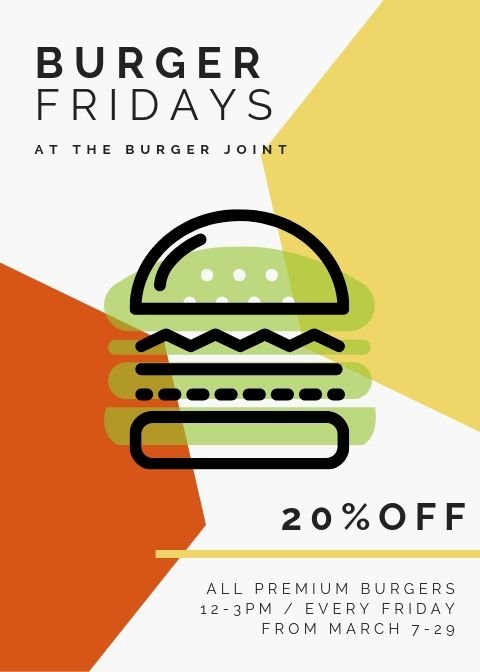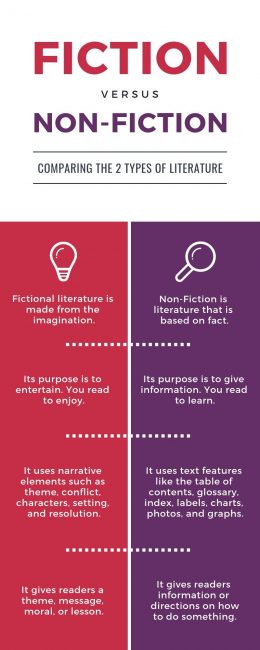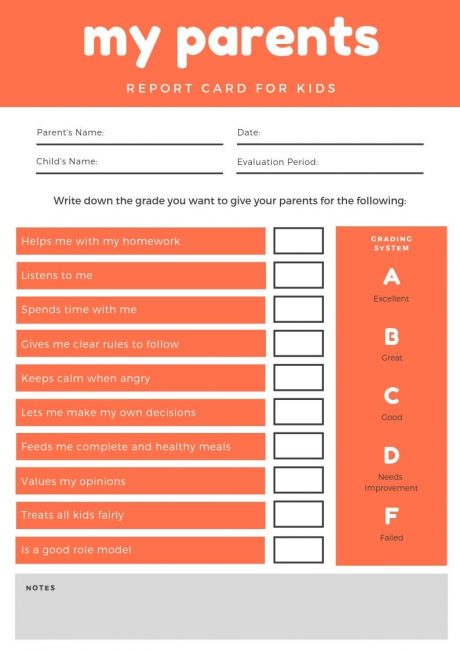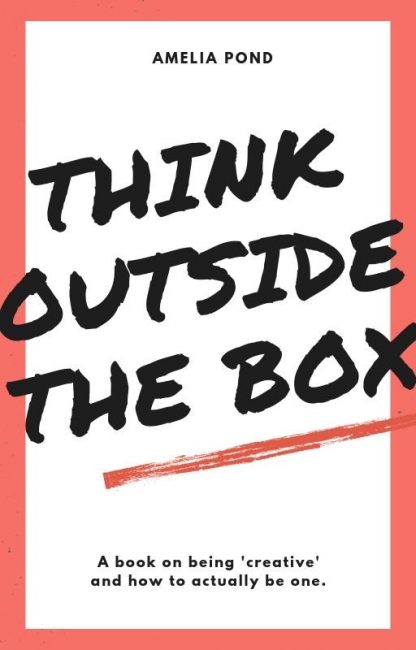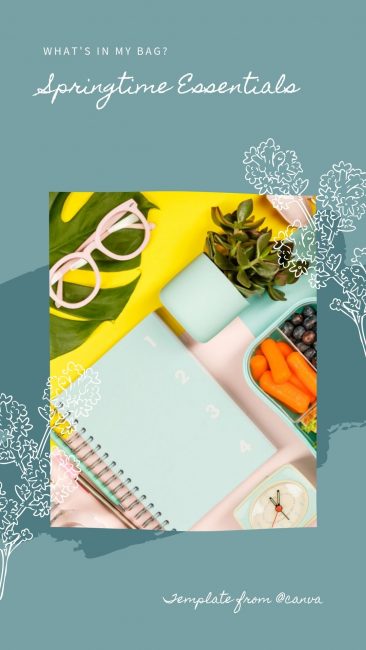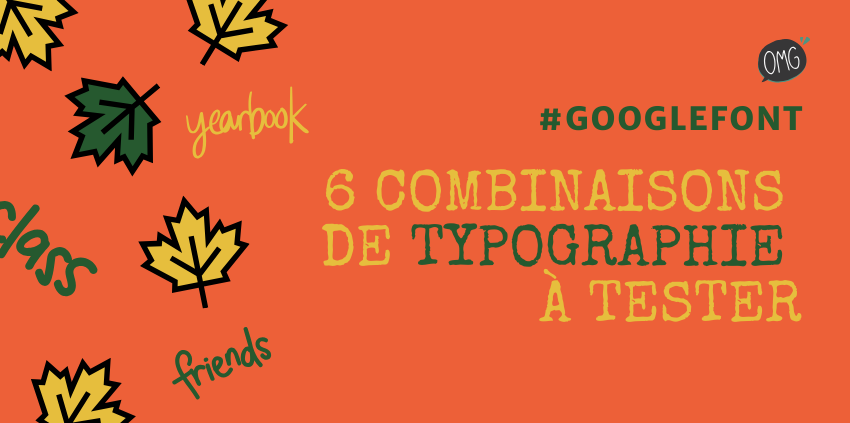
Google Fonts : 6 combinaisons de typographie à tester
Lorsqu’il est question de sélectionner les polices utilisées dans un projet, de nombreux graphistes se rendent sur Google Fonts, un service d’hébergement gratuit de polices d’écriture sous licence libre.
S’ils peuvent y trouver de l’inspiration, leur mission sera bel et bien de choisir les bonnes combinaisons de typographies pour leurs projets créatifs, celles-ci comptant parmi les éléments majeurs d’un bon design.
Aussi, nous ne pouvons qu’inviter les graphistes à tester les 6 associations de polices ci-dessous puisqu’elles fonctionnent plutôt bien.
Il faut l’avouer, à première vue, la combinaison des typographies Montserrat et Oswald n’apparaît pas très probante.
Pourtant, c’est justement de la dichotomie entre les deux polices qui donne un véritable intérêt sur le plan du design.
En effet, la typographie Montserrat — clin d’œil à la typographie urbaine du début des années 1900 — se caractérise par l’absence d’empattement et un espace généreux entre les lettres.
Au contraire, la police Oswald a de légers empattements et l’espacement entre les lettres se veut étroit. Mais le mix fonctionne parfaitement…
Pour trouver de bonnes combinaisons de typographie, il ne faut parfois pas hésiter à sortir un peu des sentiers battus.
Ainsi, l’association Merriweather et Special Elite fonctionne à merveille dès lors que vous n’utilisez pas nécessairement les polices telles qu’on l’entend.
En effet, privilégiez la police Merriweather pour les titres alors que la typographie Special Elite — qui imite une police de machine à écrire — sera utilisée pour le corps du texte. Idéal pour attirer l’œil sur vos projets créatifs.
Les polices manuscrites comme Homemade Apple confèrent un vrai charme à une création mais il faut admettre qu’elles ne sont pas toujours très lisibles.
C’est pourquoi une bonne combinaison de typographie consiste à les associer à une police percutante et clairement lisible comme Raleway.
Bien évidemment, Homemade Apple a vocation à attirer l’œil et doit être utilisé avec parcimonie, pour un titre par exemple. Pour les informations-clés, Raleway prend le relais et assure que le lecteur puisse les consulter sans difficulté.
Certaines typographies nécessitent de l’audace pour être utilisées dans des projets de création graphique. C’est le cas de Permanent Marker — inspirée de l’écriture des feutres marqueurs — tant cette police occupe l’espace et prend le dessus sur le reste des éléments d’un projet.
Aussi, il est particulièrement intéressant de l’associer à une police qui soit à la fois décontractée et élégante comme Open Sans.
L’alliance entre les deux typographies est ce qu’il vous faut si vous désirez que votre travail se démarque. C’est d’ailleurs pourquoi cette combinaison est fréquemment utilisée pour des affiches…
Si vous désirez amener un peu de fantaisie dans vos créations, la police Sniglet est à connaître. Tout en rondeurs, elle se veut parfaite pour des titres que vous voulez percutants.
Elle peut très aisément s’associer à la typographie Cabin qui offre là aussi des rondeurs même si elles sont plus subtiles. Voilà d’ailleurs ce qui en fait davantage la police complémentaire que la police principale d’un projet créatif.
Il existe de nombreuses combinaisons de typographie qui méritent d’être testées dans vos projets si vous êtes graphiste. Vous pouvez toutefois débuter par les 6 que nous vous avons proposées ici puisqu’elles vous offriront d’excellents résultats en matière de design.